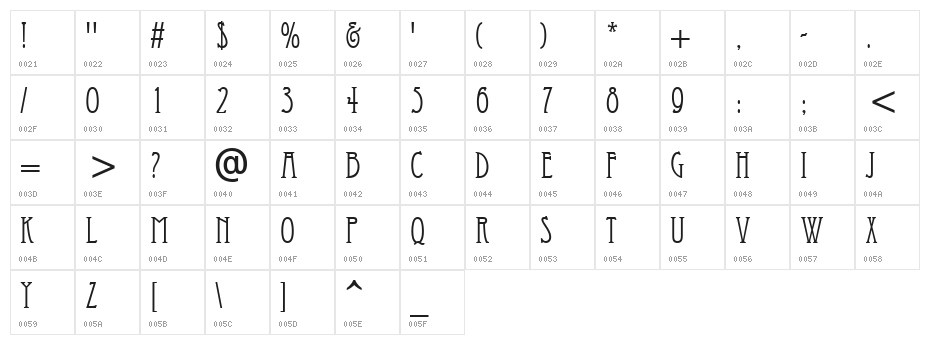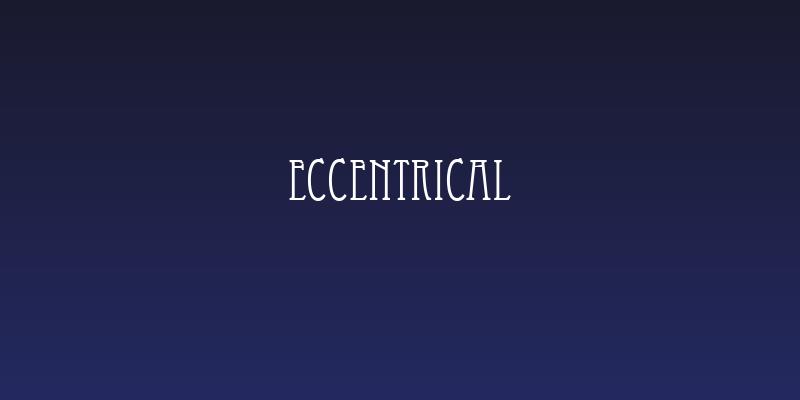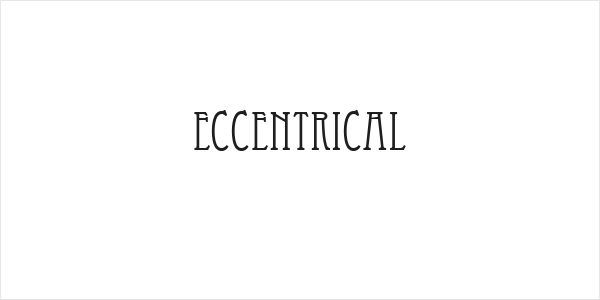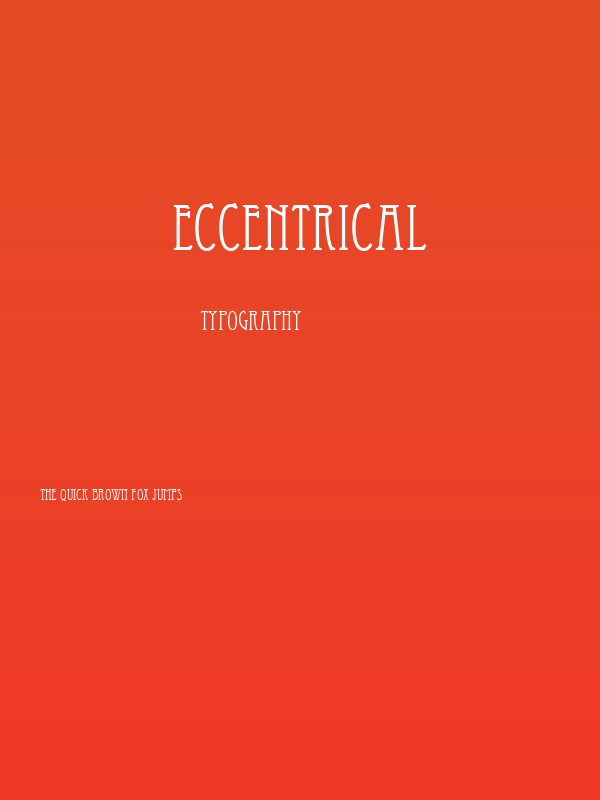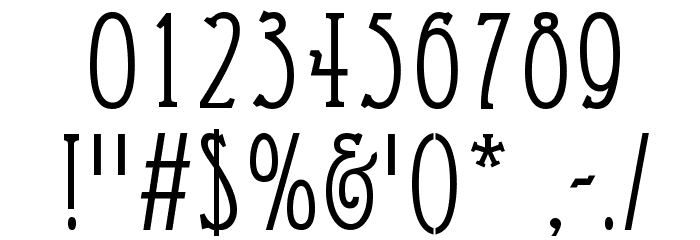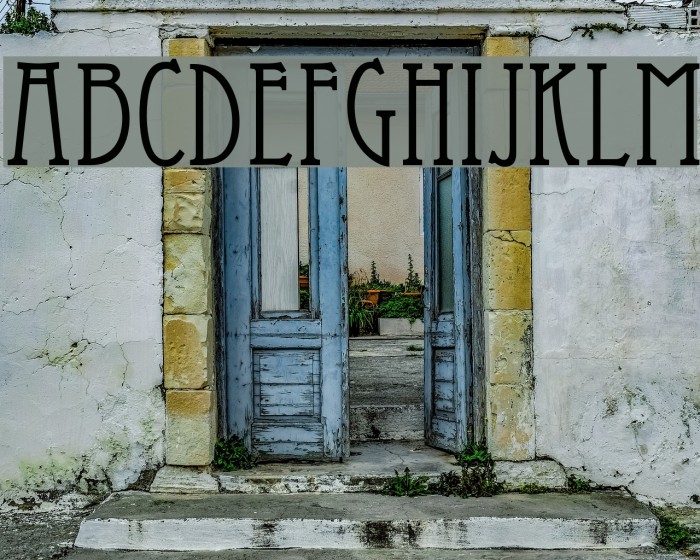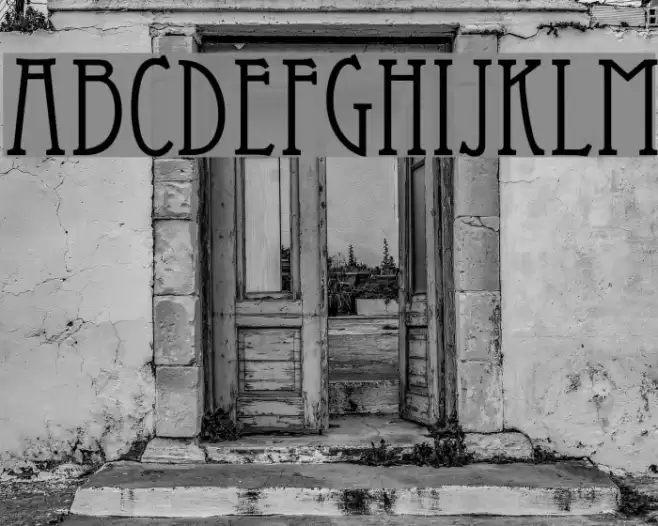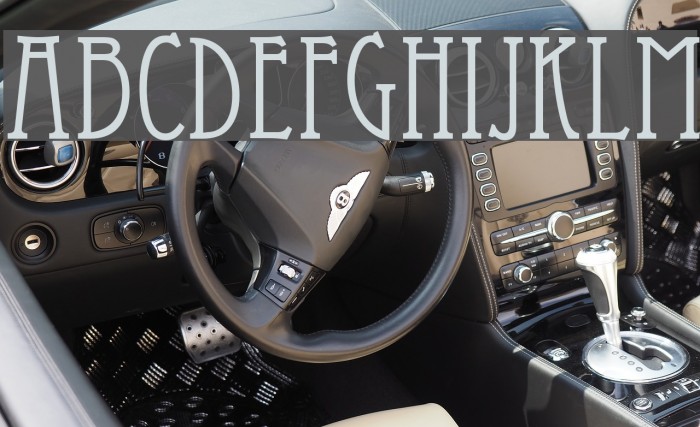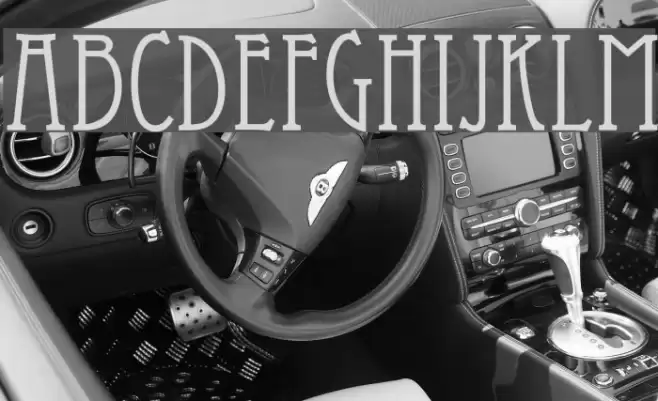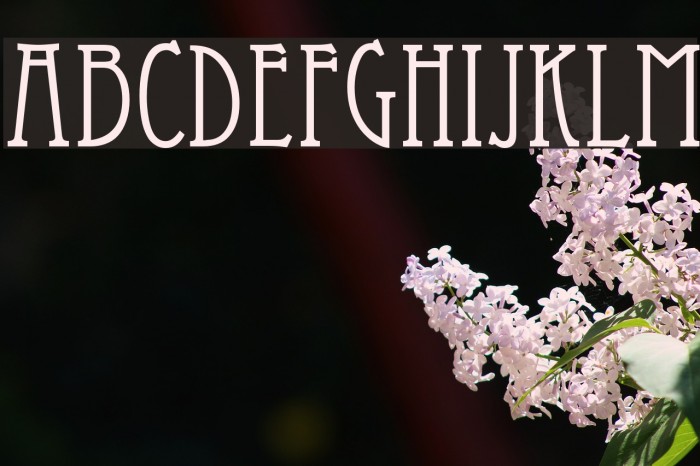
Eccentrical Font
ECCENTRICAL 大文字
ECCENTRICAL 小文字
ECCENTRICAL その他の文字
| おすすめプロジェクト | Ideal for creative projects such as posters, invitations, branding, and any design work that requires a touch of whimsy and uniqueness. |